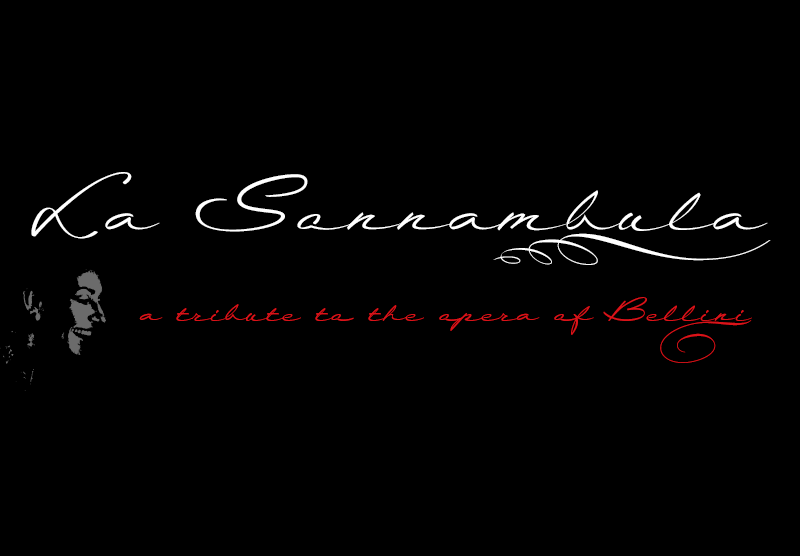
La Sonnambula Font
A fonte La Sonnambula é ideal para quem busca uma escrita elegante e autêntica. Desenvolvida pela defharo com base na famosa ópera La Sonnambula de Vincenzo Bellini, que Maria Callas interpretou no teatro de Milão em 1957, essa fonte é perfeita para criar títulos sofisticados ou textos em estilo calligrafia. Inspirada no mundo fascinante da música lírica e na bela interpretação de Maria Callas, La Sonnambula oferece uma escrita arredondada e charmosa que traz um toque refinado a qualquer projeto. Além disso, a fonte inclui o símbolo Bitcoin (b#), tornando-a ainda mais versátil para criações digitais e interativas. A defharo cuidadosamente construiu La Sonnambula para dar vida às palavras ao longo do texto, desde as frases mais simples até os textos de longa extensão. Seja para um projeto de design editorial, logotipo ou qualquer aplicação visual que valorize a escrita manual e seu encanto, a fonte La Sonnambula é uma escolha ideal.